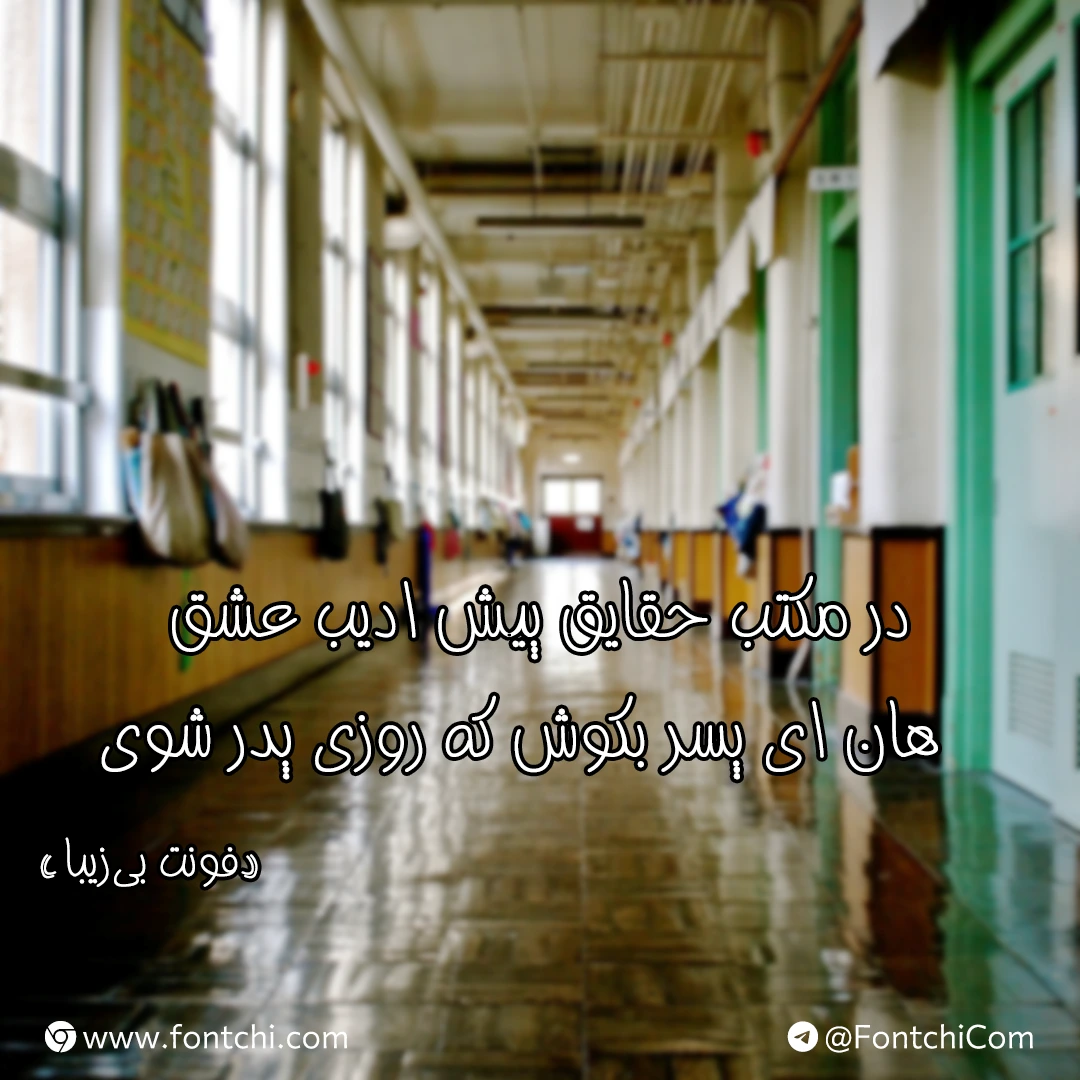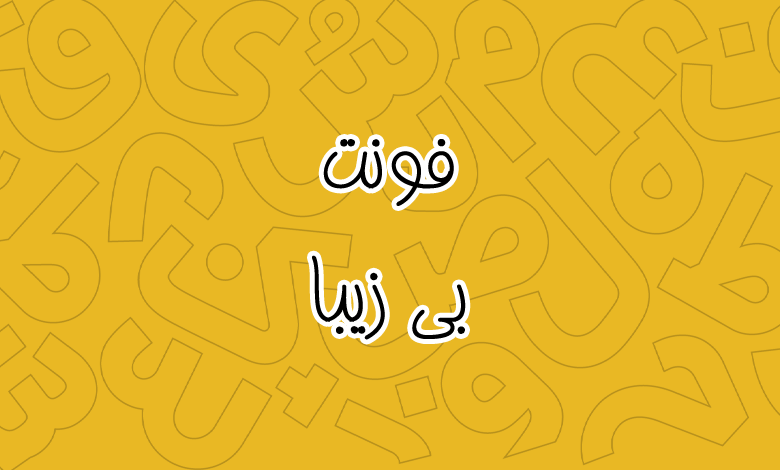
فونت بی زیبا (B Ziba)
فونت بی زیبا (به انگلیسی: B Ziba) یکی دیگر از فونت‌های فارسی طراحی شده توسط برنا رایانه در دهه ۷۰ است که دارای ظاهری فانتزی می‌باشد. این فونت دارای ظاهری دست‌نویس است و نقطه‌های در آن برخلاف سایر فونت‌های سری B دارای ظاهری متفاوت هستند.
با اینکه این فونت برای زبان فارسی ساخته شده، اما از زبان عربی نیز پشتیبانی می‌کند. تنها ایراد آن نیز عدم پشتیبانی کامل از اعداد فارسی است که برای اعداد «۰۴۵۶» از اعداد عربی استفاده شده است. در ادامه می‌توانید پیش‌نمایش فونت زیبا را مشاهده کرده و با مشخصات بیشتری از این قلم آشنا شوید.
سبکه نقطه‌گذاری در فونت بی زیبا بدین‌صورت است که نقاط دوتایی به شکل افقی در کنار هم قرار دارند، اما نقاط سه‌تایی به شکل عمودی مرتب شده‌اند. البته این سبک نقطه‌گذاری کلی نیست، متناسب با ترکیبات و نوع حروفی که استفاده شده باشد در برخی موارد نقاط سه‌تایی اینطور تایپ می‌شوند.
ویژگی دیگر فونت رایگان بی زیبا ساختار دست‌نویس و فانتزی آن است. از این‌رو می‌تواند انتخاب مناسبی برای کارهای گرافیکی نمایشی، به‌ویژه در حوزه کودک و نوجوان باشد. این فونت فقط از یک وزن معمولی Regular پشتیبانی می‌کند.
فونت بی زیبا برای زبان انگلیسی از فونت پیش‌فرض تاهوما استفاده می‌کند. در نرم‌افزارهای گرافیکی مانند فتوشاپ نیز می‌توانید از حالت OutLine این قلم استفاده کنید.